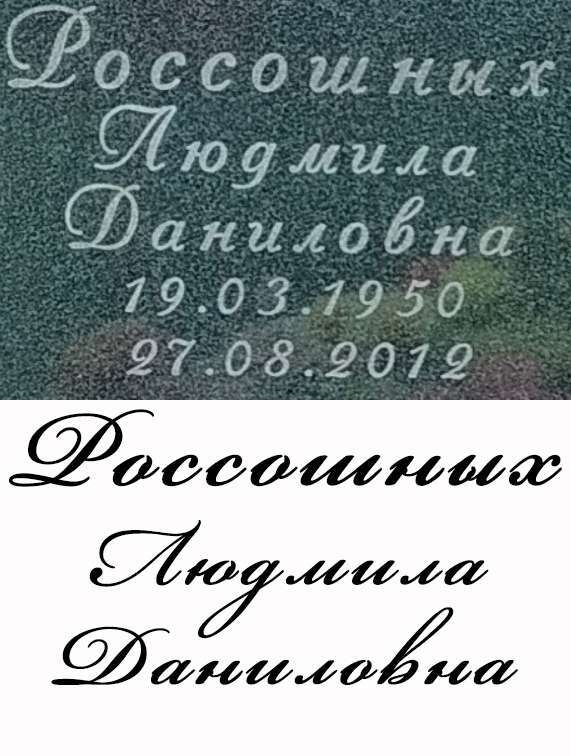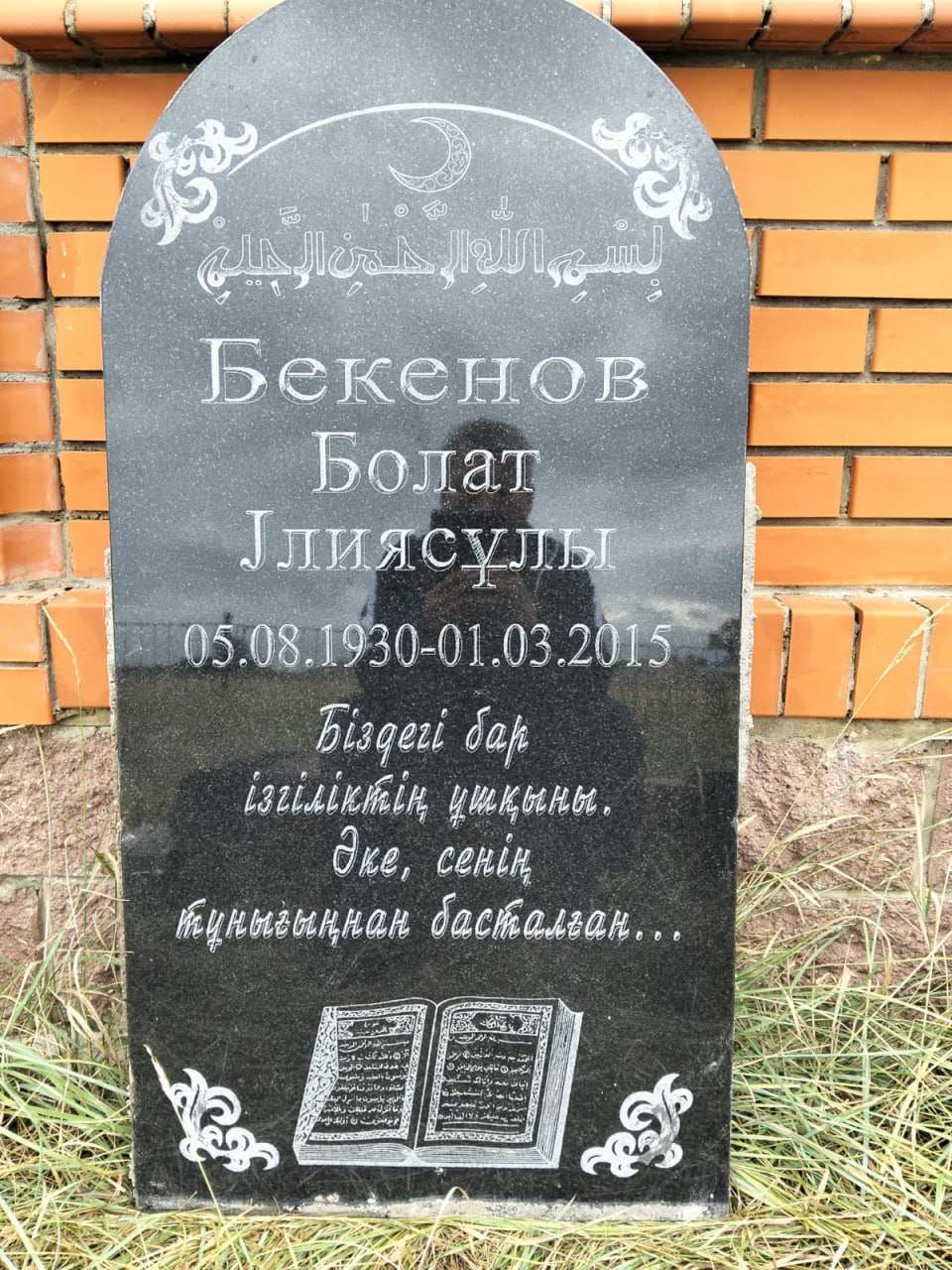
leekbez Опубликовано 25 августа https://cloud.mail.ru/public/Yerx/Qt1fFtE9o кто поможет также шрифт сделать, пожалуйста
antei Опубликовано 28 августа (изменено) Приветствую. Подскажите шрифт, вроде как Bickham Script One, но не один в один. Как исправить? Или может есть готовый у кого? Изменено 28 августа пользователем antei
igors Опубликовано 28 августа 3 часа назад, antei сказал: Ну так подскажи, какой это шрифт да делайте этот шрифт ни кто даже внимание не обратит зачем Вам эти приплюхнутые завароты
Romeo Опубликовано 16 сентября Коллеги,помогайте пжста..первый раз такой шрифт виду.кто что подскажет по нему. Заранее спасибо
aazt Опубликовано 22 сентября (изменено) Помогите найти шрифт! Carolina нашел )) Изменено 22 сентября пользователем aazt 1
Romeo Опубликовано 22 сентября В 16.09.2026 в 18:39, Romeo сказал: Коллеги,помогайте пжста..первый раз такой шрифт виду.кто что подскажет по нему. Заранее спасибо на 95 % PT Serif
Alexsey Опубликовано 24 сентября Доброе утро, подскажите пожалуйста что за шрифт
антропов роман Опубликовано 8 октября (изменено) 18 часов назад, fenix сказал: Доброе утро, подскажите пожалуйста что за шрифт Ты, вроде, не вторую ночь замужем то... Очевидно ж, что ручник ... 4 часа назад, Анжела92 сказал: Подскажите пожалуйста название шрифта Так же явно что ручник-лабух. Разные -е- в одной строчке...и -у- в эпитафии.. Ну и в целом пластика и пропорции явно не с компа от профи-шрифтовиков... та ещё, постсовковая "школа" ... даже странно при недавней дате смерти такое встретить... Изменено 8 октября пользователем антропов роман 1
designer Опубликовано Четверг в 10:31 помогите определить шрифт у надписи «Санкт-Петербург»! Заранее благодарен!
aazt Опубликовано Суббота в 11:01 коллеги, подскажите пожалуйста что за шрифт
TatyanaPi Опубликовано Суббота в 16:36 Даты похожи на шрифт a_FuturaOrto, а ФИО - a_FuturicaExtraBlack 1